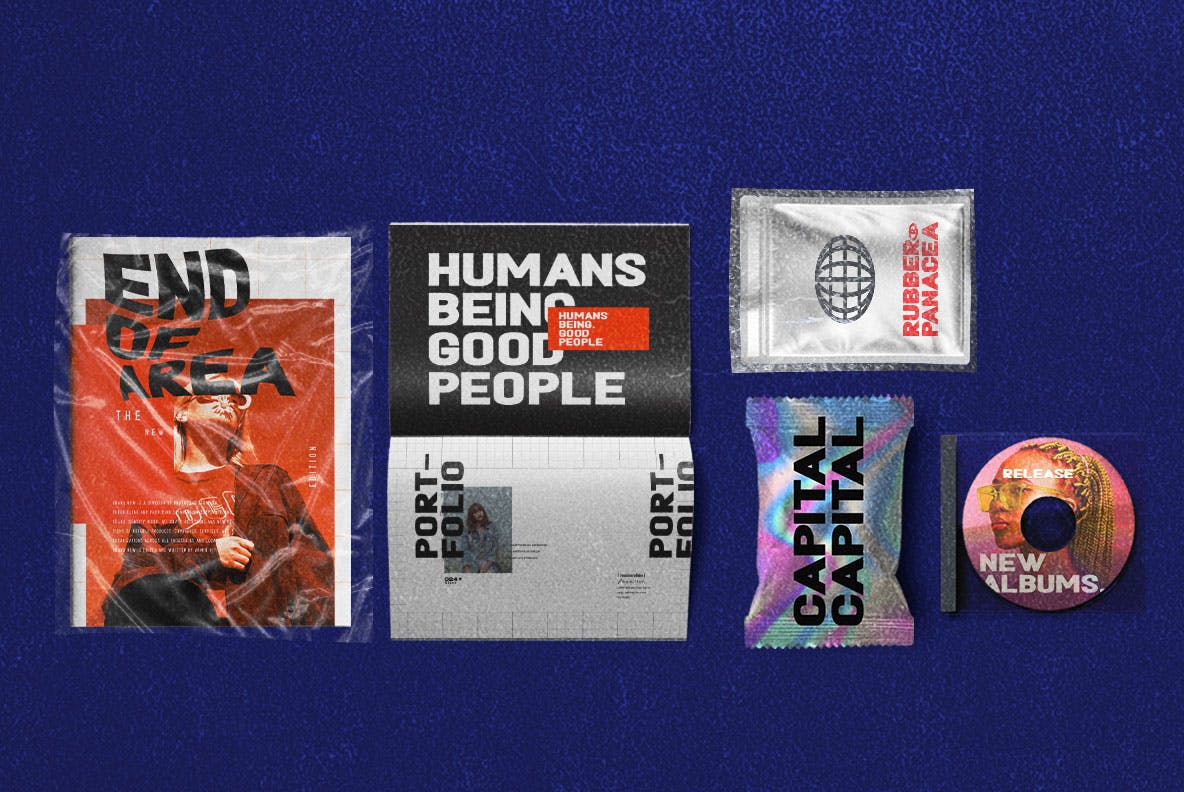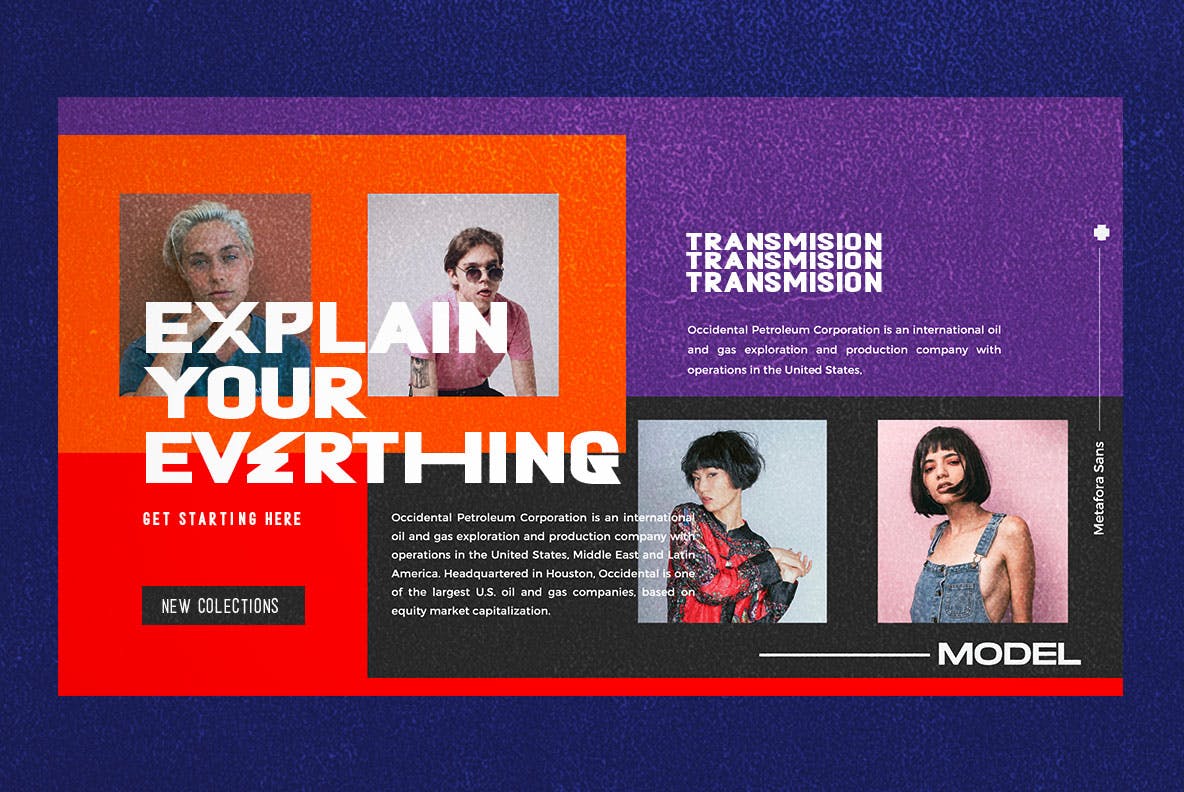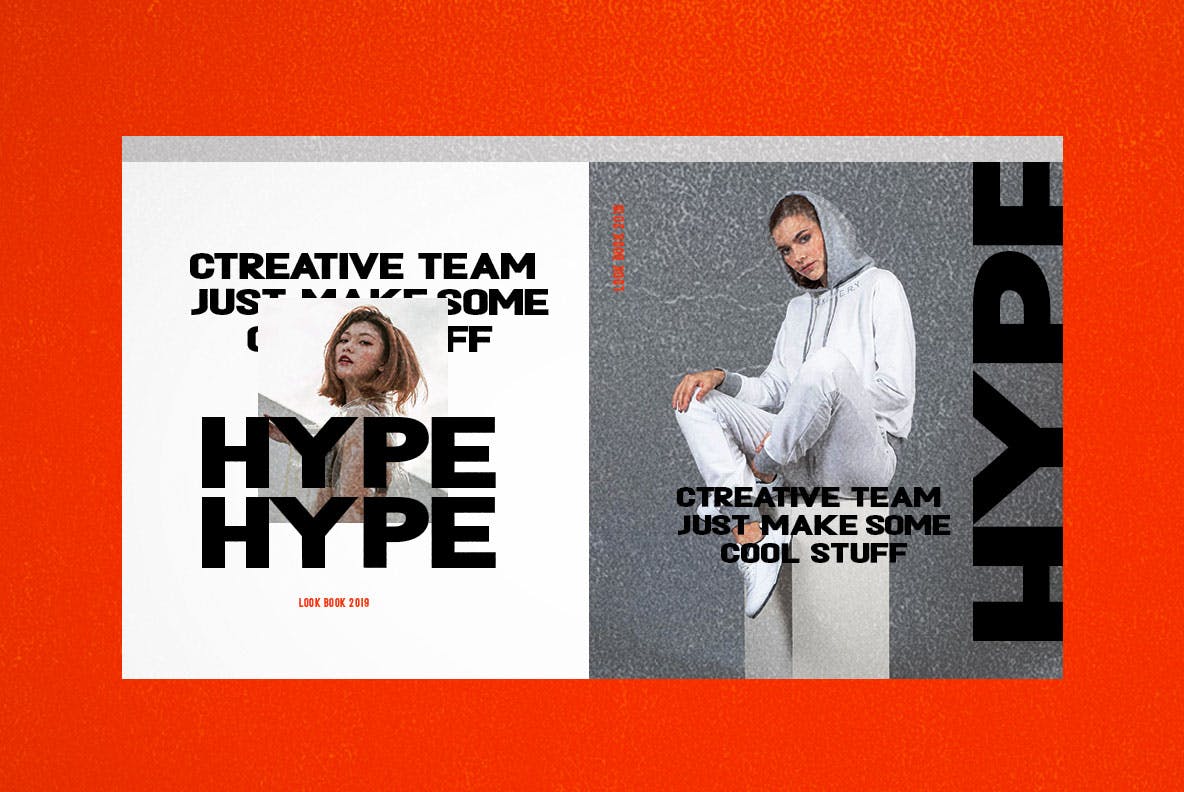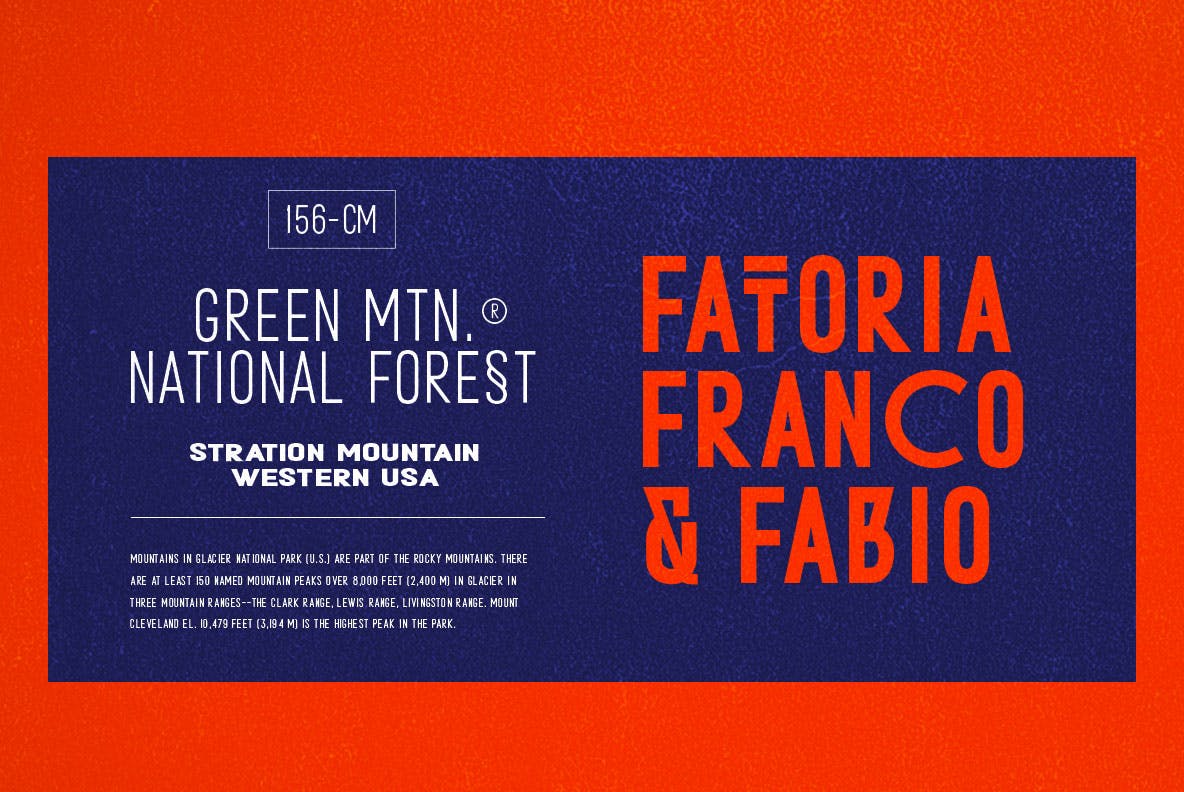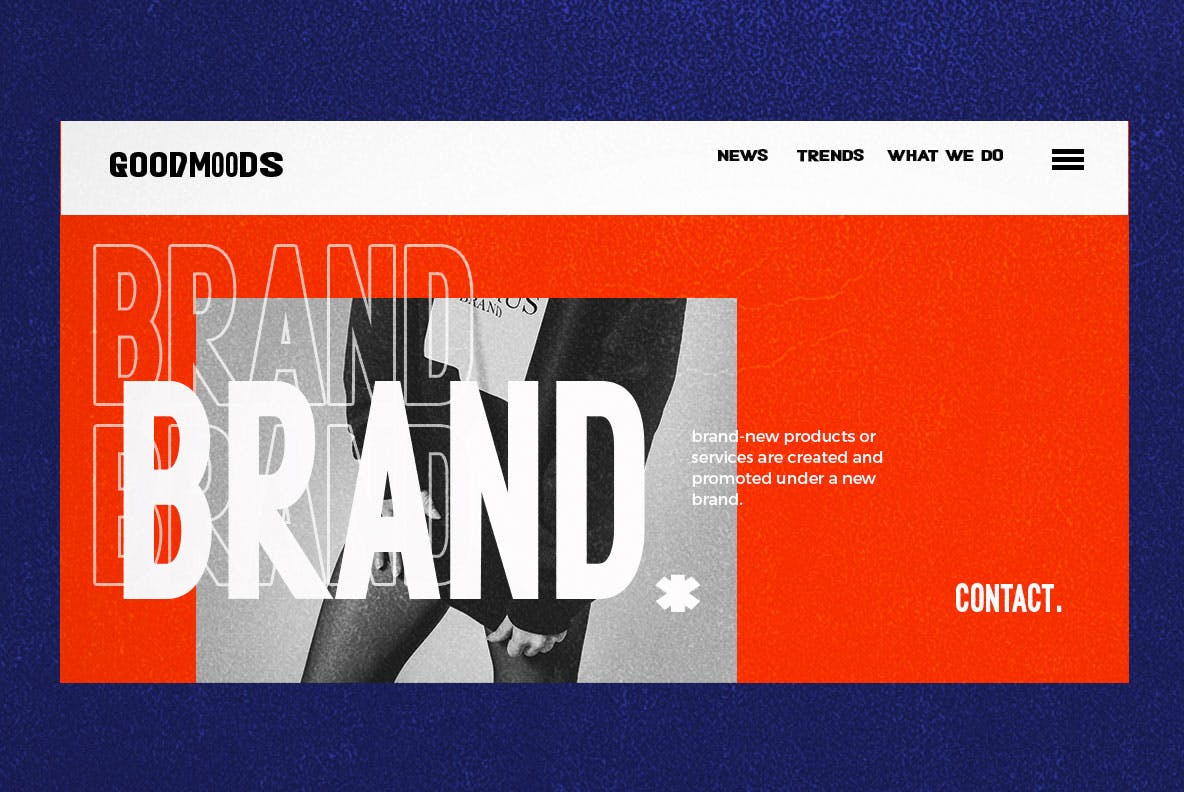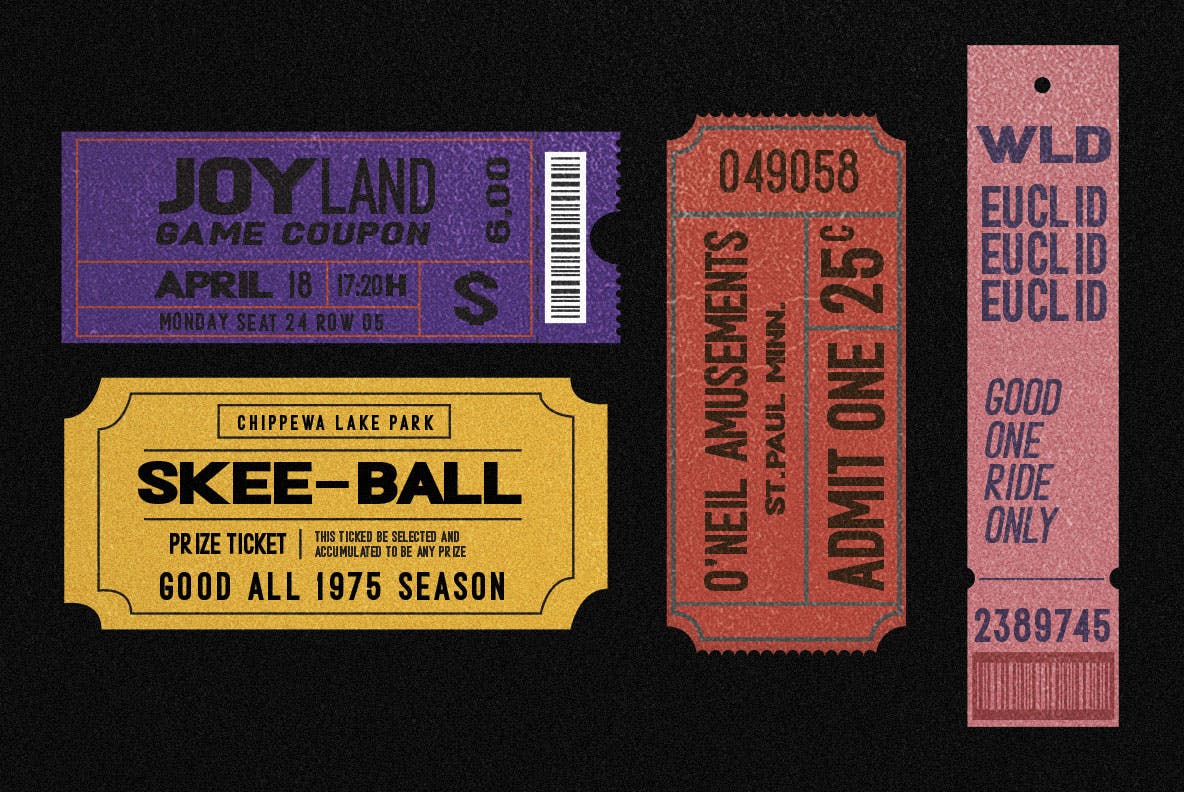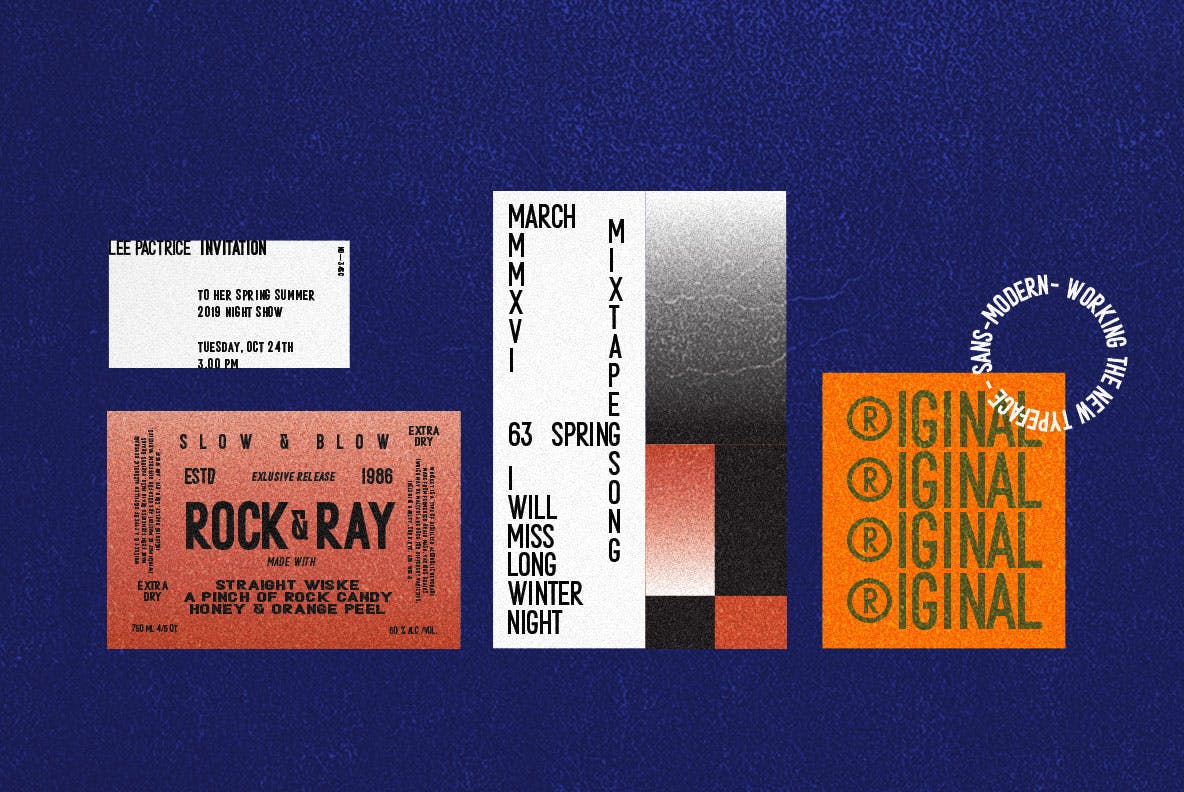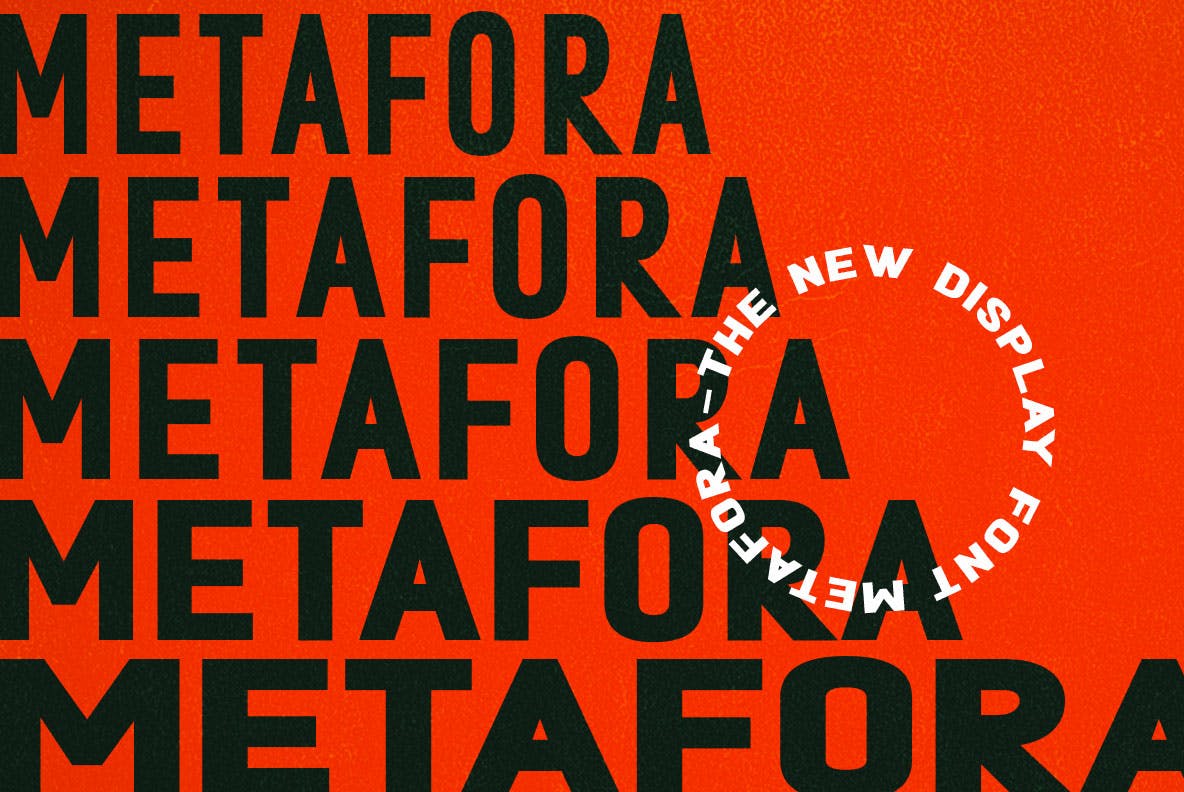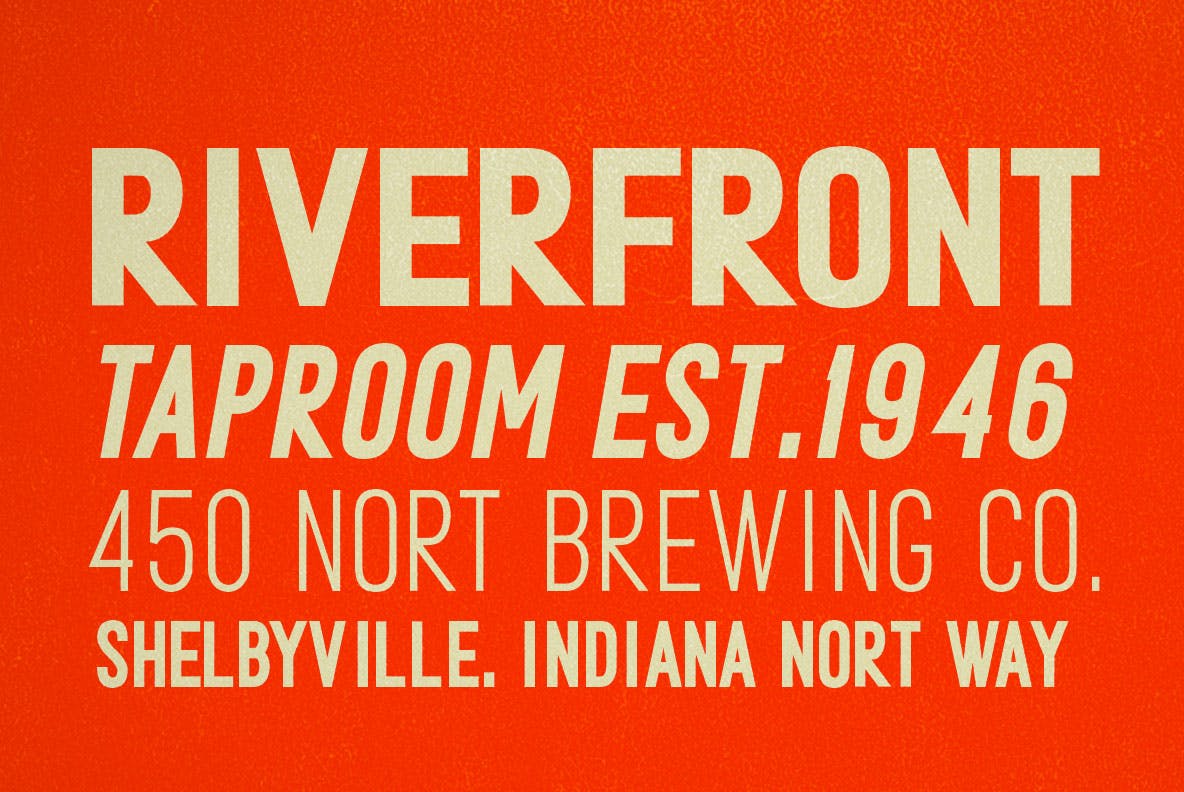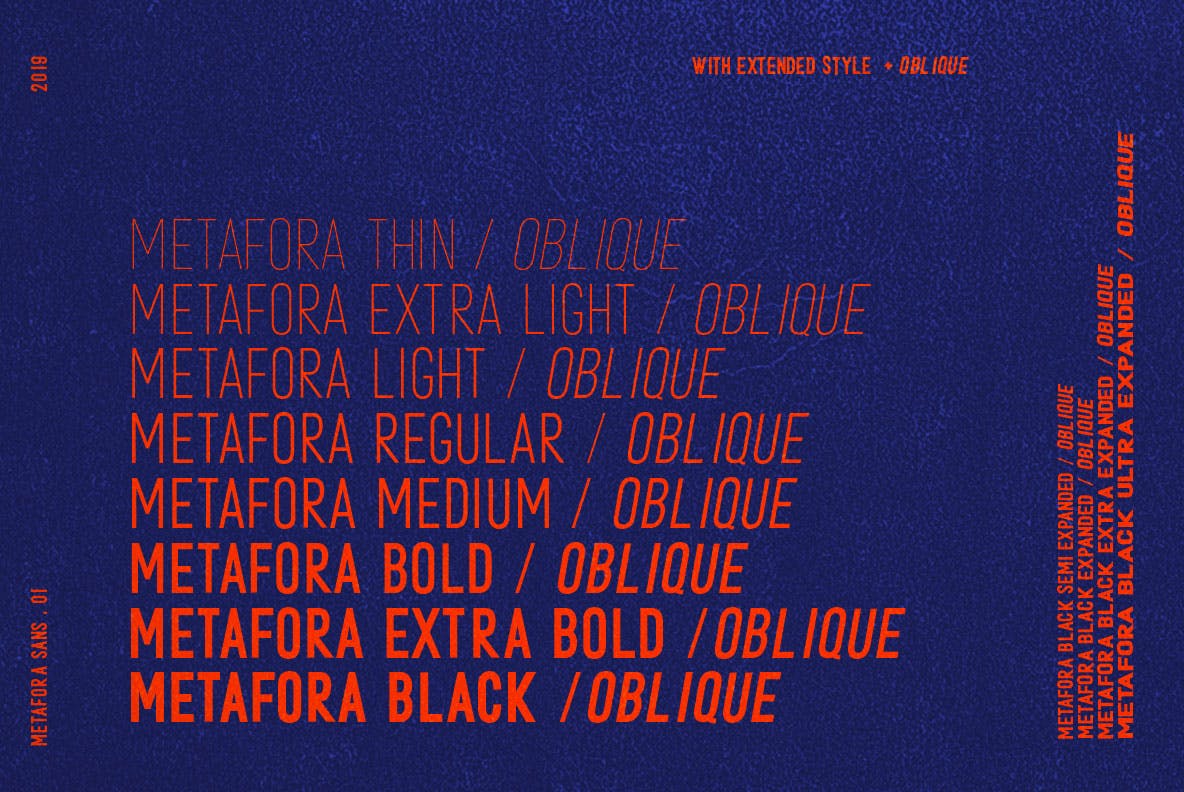
Metafora Modern Sans Serif Font
فونت متافورا یک انتخاب مناسب برای طراحی‌های مدرن است.
فونت متافورا سنس یک خانواده نمایش معاصر است که برای کارکردهای چندمنظوره طراحی شده و بهترین عملکرد را در هر زمینه چاپی و دیجیتال، از جمله طراحی لوگو، هویت برند، وب‌سایت‌ها، بسته‌بندی، پوستر و تیترها دارد.
ویژگی‌ها:
• مجموعه‌های استایل جایگزین
• حروف الفبای لاتین A-Z و a-z
• اعداد و نمادها
• لیگاتور
• پشتیبانی از چند زبان